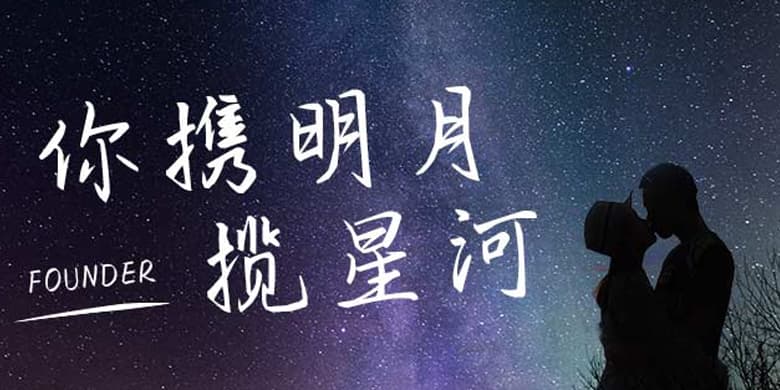
品牌:方正手迹设计师:尚正中发行时间:2020字库编码:大陆简体(GB2312-80)分类:常规书写·硬笔字体属性:精品字
英文名称:FZSJ-NIXMYLXH.TTF
一款舒适度超强的手写楷体,中宫宽松,收笔有秩,粗细对比适当,结构严谨。适用于文艺类的书刊、品牌广告和产品包装设计,以及社交网络的个性化用字。